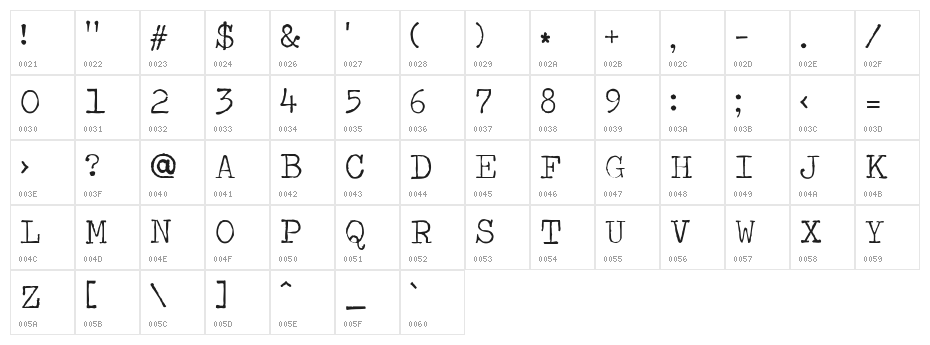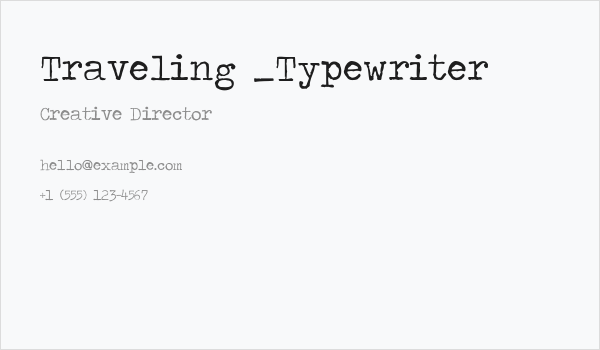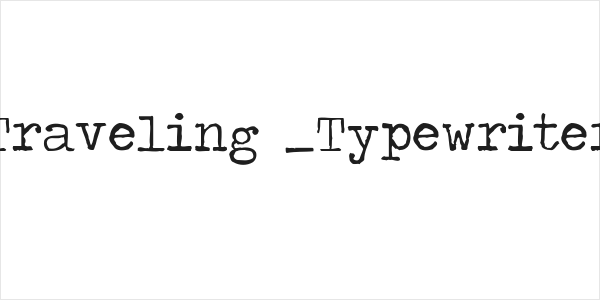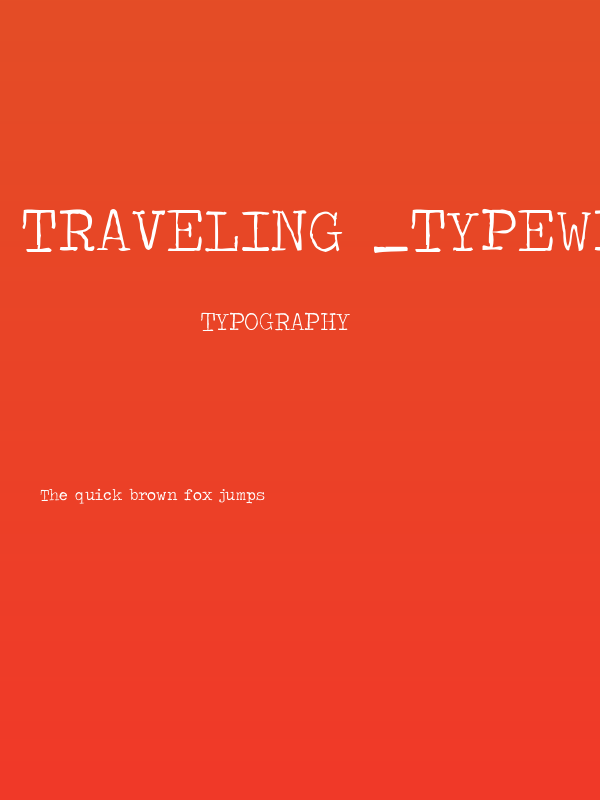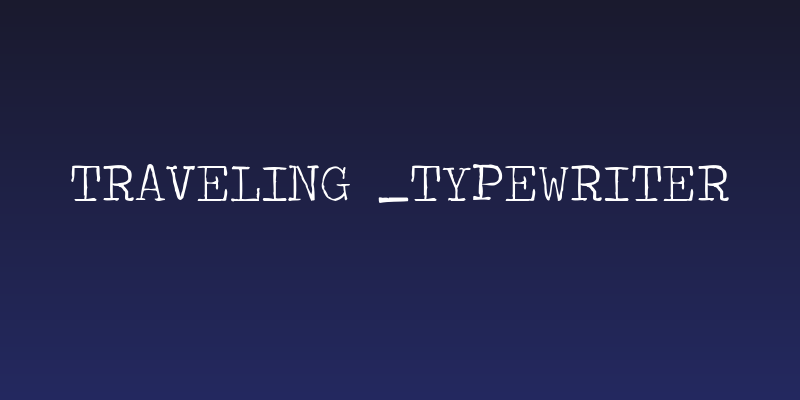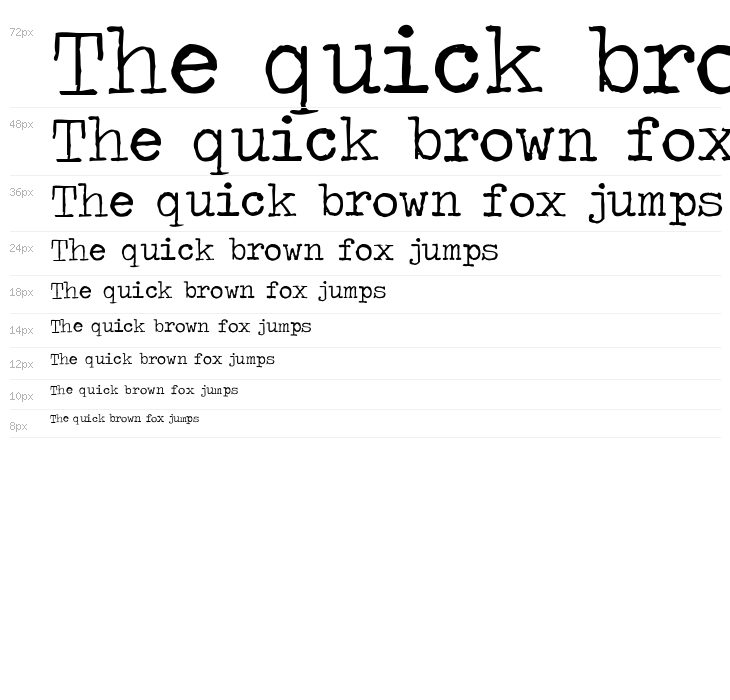
Traveling _Typewriter Font
| Caz de utilizare | Headlines, Logos, Creative writing |
| Proiecte propuse | Ideal for projects that require a retro or vintage aesthetic, such as historical documents, typewriter-themed designs, or creative writing projects. |